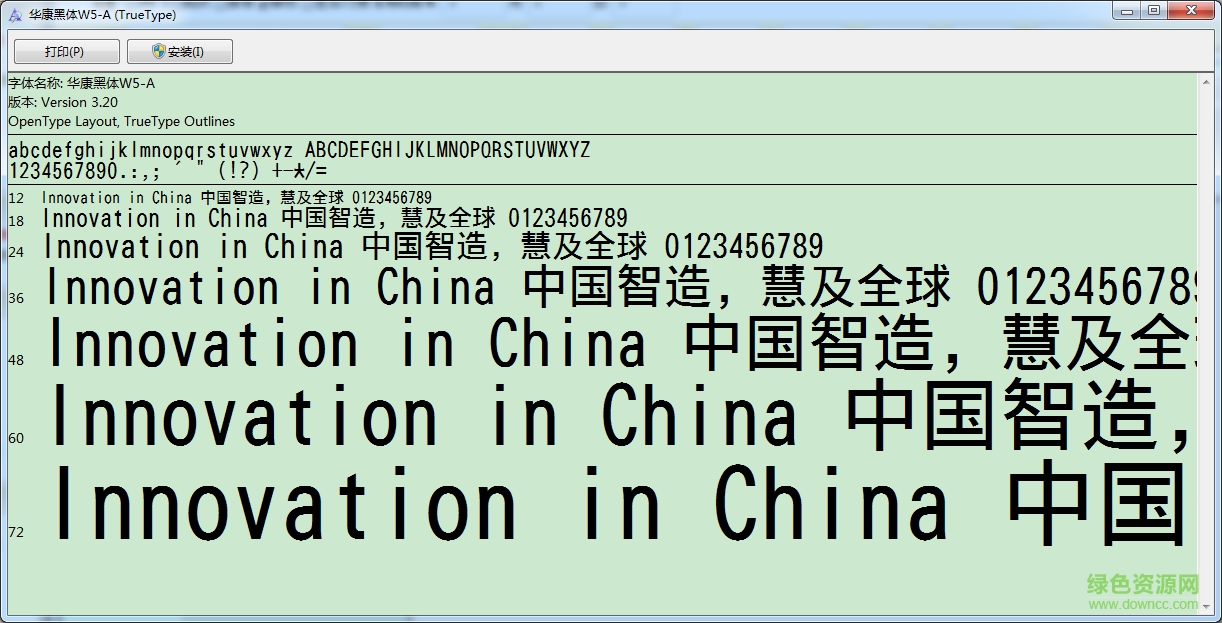
dfheiw5是什么字體?dfheiw5-a字體是華康黑體W5-A字體,該字體沒有襯線裝飾,筆畫干凈,字形醒目,極具現(xiàn)代感,還非常易于閱讀,需要的朋友歡迎在綠色資源網(wǎng)下載!
黑體字在字架上吸收了宋體字結構嚴謹?shù)膬?yōu)點,在筆畫的形狀上把橫畫加粗且把宋體字的聳肩角削平為等線狀,形成橫豎筆畫粗細一致,變宋體字的尖頭細尾和頭尾粗細不一的筆畫為方形筆畫。
漢字的黑體是在現(xiàn)代印刷術傳入東方后依據(jù)西文無襯線體中的黑體所創(chuàng)造的。由于漢字筆劃多,小字的黑體清晰度較差,所以一開始主要用于文章標題,但隨著制字技術的精進,已有許多適用于內文的黑體字型。